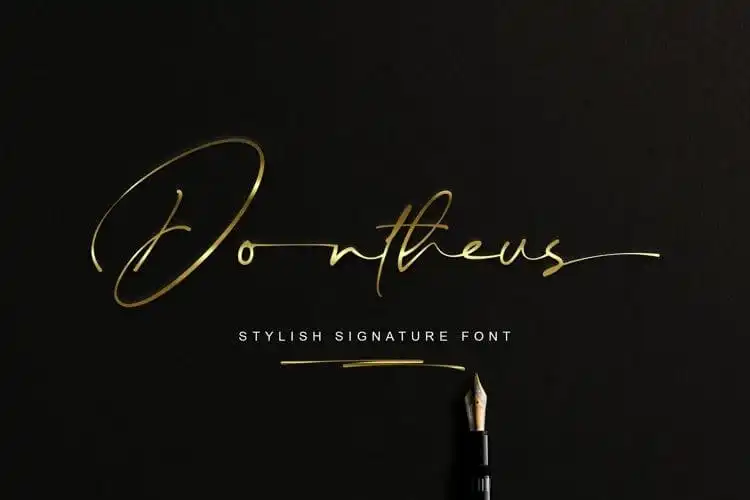
Dontheus Handwritten Font – Download Grátis
A fonte ‘Dontheus Handwritten Font’ é uma delícia para os olhos, com traços elegantes e delicados que não deixam ninguém indiferente. Ela é perfeita para criar mensagens respeitosas e estilo sofisticado em qualquer projeto de design. Seja para criação de logotipos ou marcas, envelopes e assinaturas, decorações nupciais, postagens de redes sociais, anúncios, embalagens de produtos, ilustrações, água-marinhas, eventos especiais ou qualquer coisa que você possa imaginar, esta fonte é perfeita. A Dontheus Handwritten Font traz elegância à qualquer design, tornando-o ainda mais especial e único. Experimente a sua versão gratuita hoje e veja como ela pode transformar seu trabalho de design em algo verdadeiramente único.